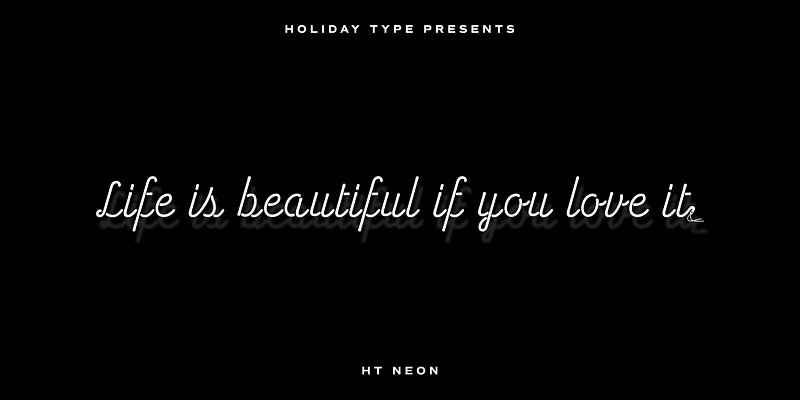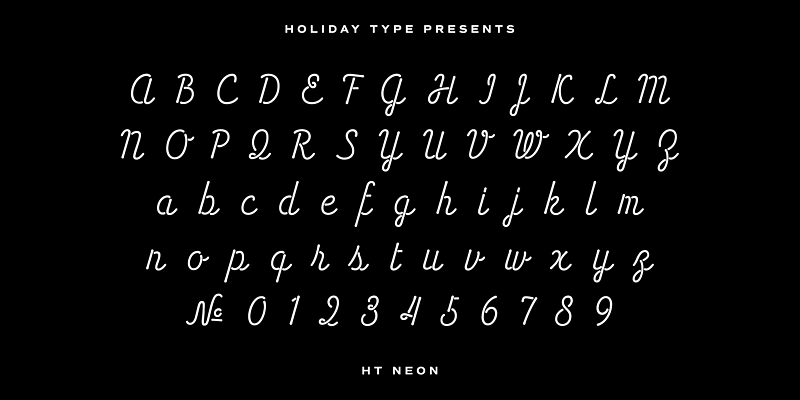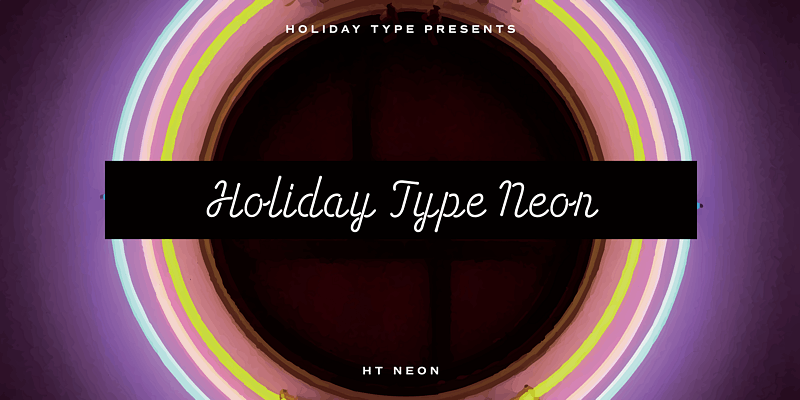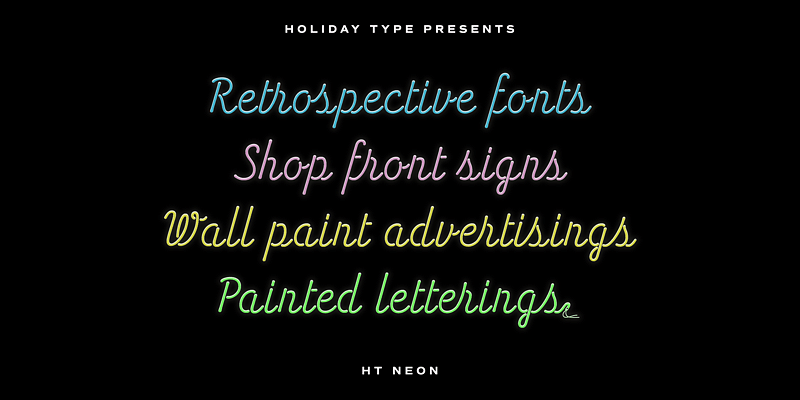
HT Neon brille comme pour nous inviter. Cette police arrondie et monoligne est très frappante, mais aussi lisible car les caractères sont disposés naturellement lorsqu’ils sont tapés.